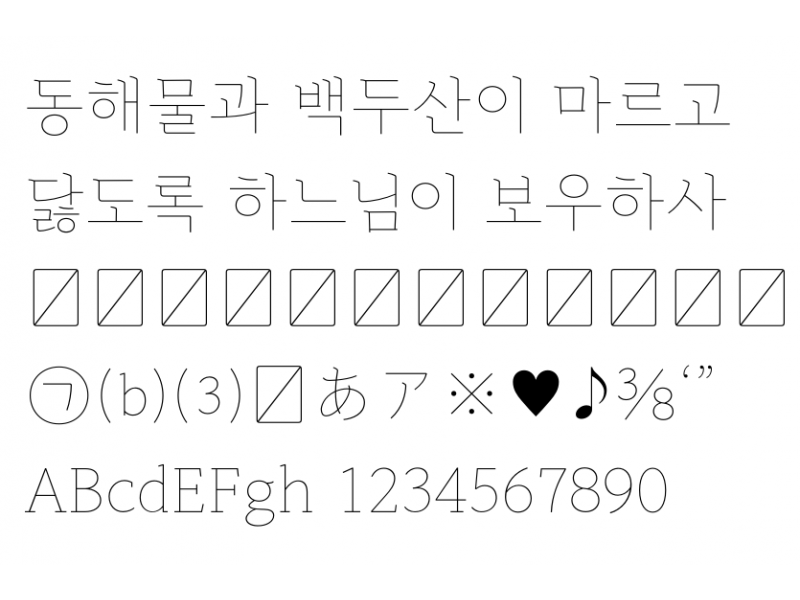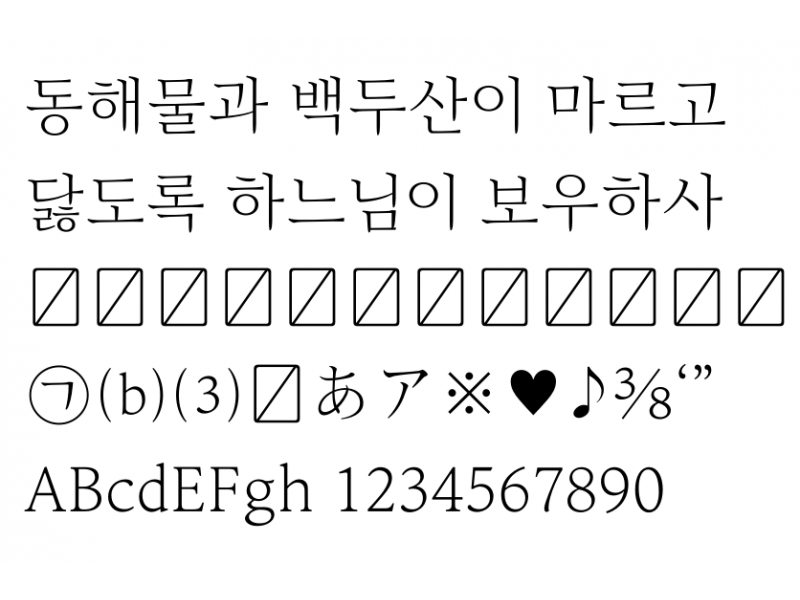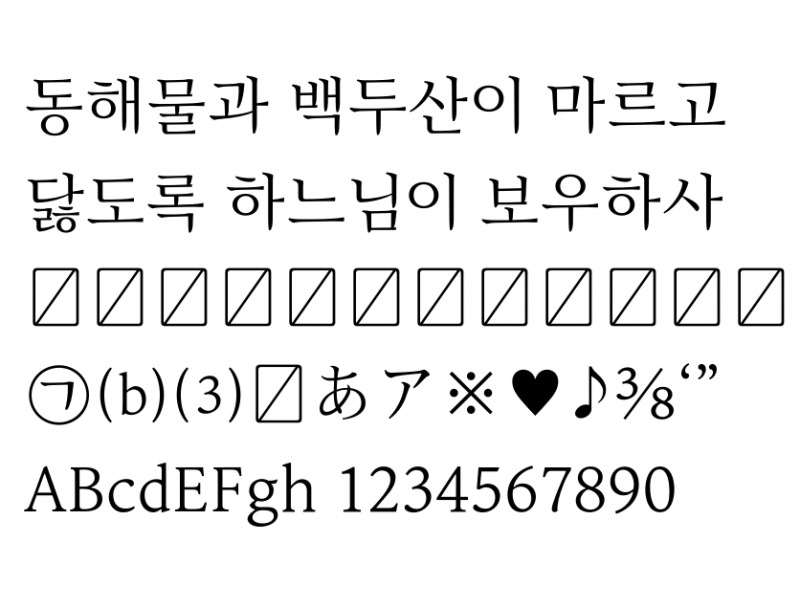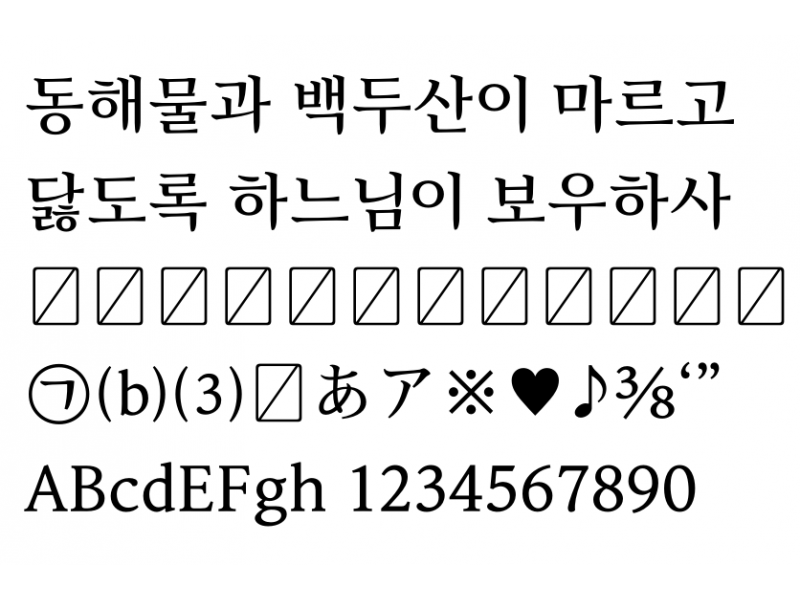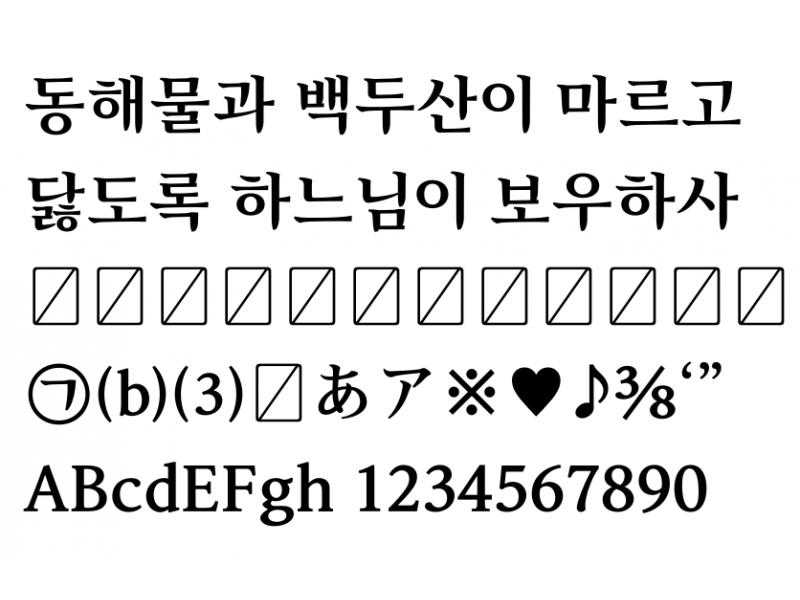
아리따 글꼴은 고딕계열의 트루타입(True Type) 글꼴이다. 홍익대학교 안상수 교수, 서울여자대학교 한재준 교수, 글꼴 디자이너 이용제 등이 제작하였고, 한글 1만1172자, 영어와 숫자 94자, KS코드 기준 특수문자 등을 포함하고 있다. > 아리따돋움, 아리따부리(2014년 추가), Arita Sans(2012년 추가, 영문글꼴)로 3가지로 구성되어 있다. thin-light-medium-semibold-bold의 5가지의 굵기를 제공한다.
긴 문장에 적합한 본문용 글꼴로 2014년 완성된 아리따 부리는 현대적인 여성의 단아하고 지적인 멋스러움을 담고 있다. 국내 최초로 머리카락같이 가는 헤어라인 서체를 개발해 기업 글꼴의 새로운 흐름을 제시한 점을 높게 평가 받고 있다.